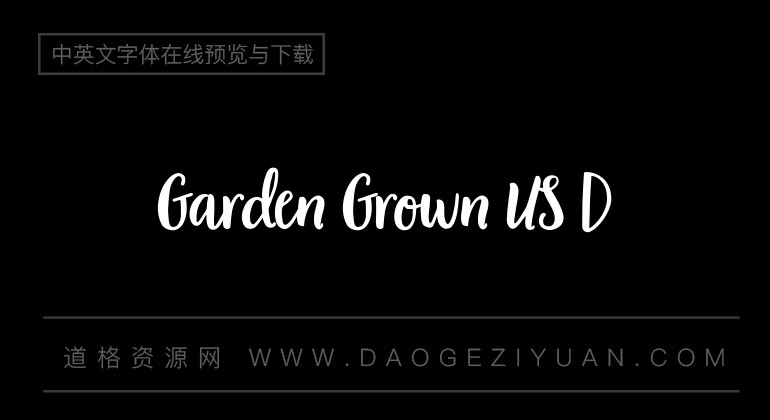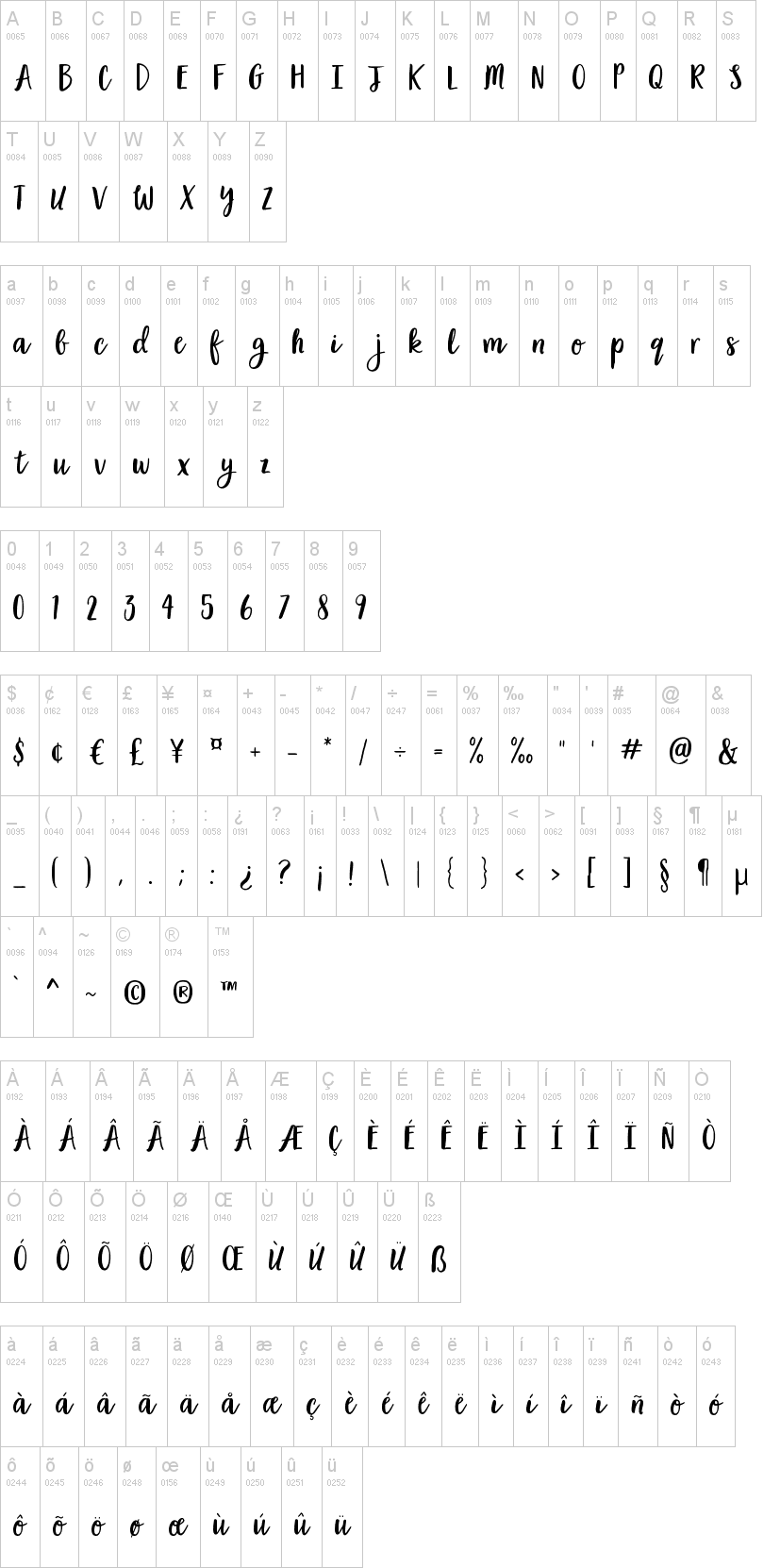
Garden Grown US D
Garden Grown US D是一款由Garden Grown字体库推出的美式手写体字体。它具有细腻、精致、细节丰富的特点,可以为您提供清晰、精美的文字效果。Garden Grown US D字体具有细腻的线条,可以帮助您创建精致、优雅的文字效果。它还具有细节丰富的特点,可以为您的文字提供独特的外观和感觉。此外,Garden Grown US D字体还具有优质的可读性,可以帮助您创建清晰的文字效果。
Garden Grown US D是一款非常不错的手写艺术字体,具有很好的视觉感,适合于文化类的宣传设计、商业类品牌的广告和产品包装设计以及个性化文字排版等较多场景。
Garden Grown US D字符映射图